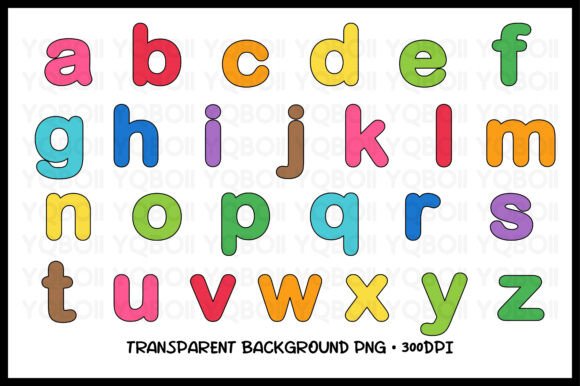
Lowercase Alphabet Letters Clipart Set
Jika anda sedang mencari aset berkualiti tinggi seperti Lowercase Alphabet Letters Clipart Set, pakej premium ini merupakan pilihan yang hebat untuk projek kreatif anda.
Dicipta dengan ketepatan, Lowercase Alphabet Letters Clipart Set menyediakan vektor yang bersih, tipografi yang licin dan lesen komersial untuk ketenangan fikiran.